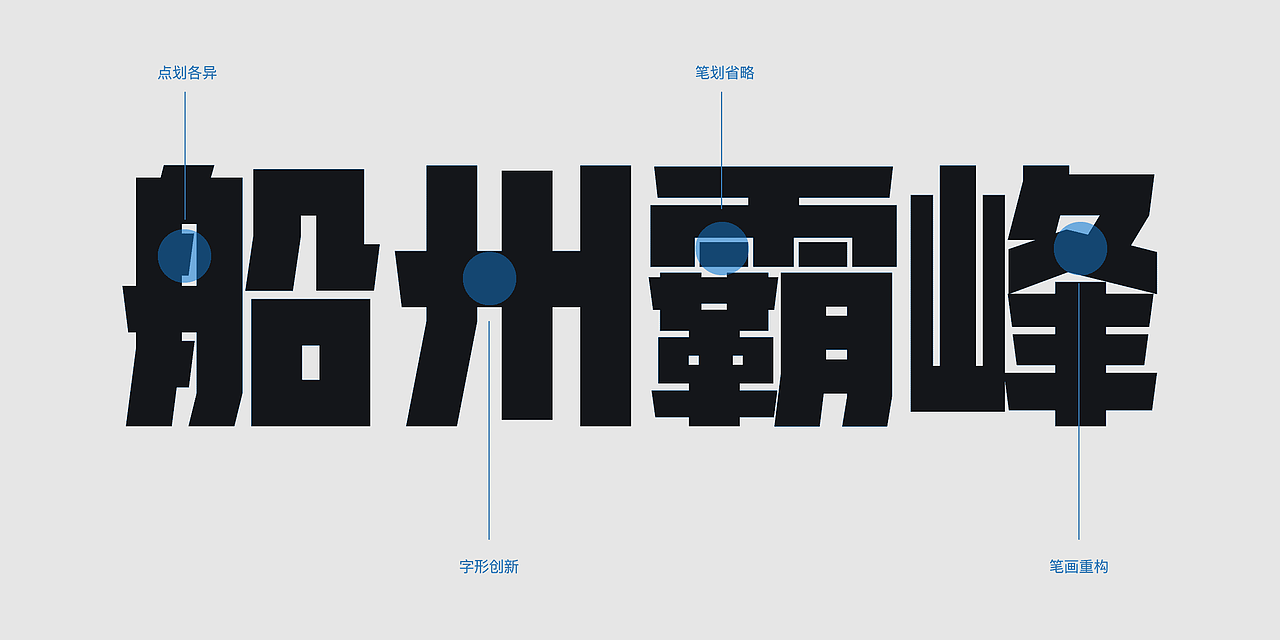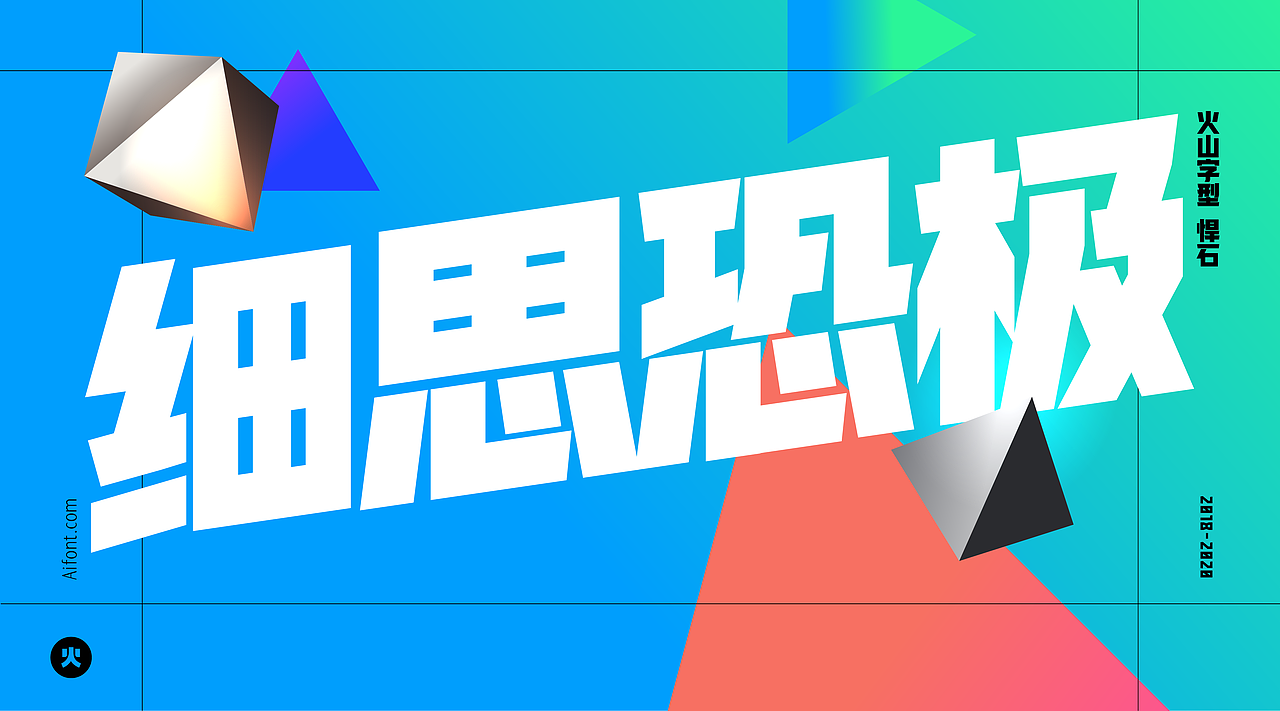
火山字型 悍石
创意型美术标题字体,在海报、广告、杂志等场景中有良好的展示效果。电商页面、公关活动、影视娱乐、互联网等行业推荐使用。
悍石,采用大中宫、小字谷的风格制作,使得整套字型视觉上呈现饱满平稳之态。作为标题类字体,字面宽度作了适当缩减,这样视觉上既保持了方块字的特征,也为横向排版节省了空间。为了在小尺寸使用时增加辩识度,对某些笔画进行断笔重构,如横画两端斜切、「禾」、「攵」等断笔,既加大了字白区域,同时也让字形张驰有度、特点鲜明,极富视觉表现力。